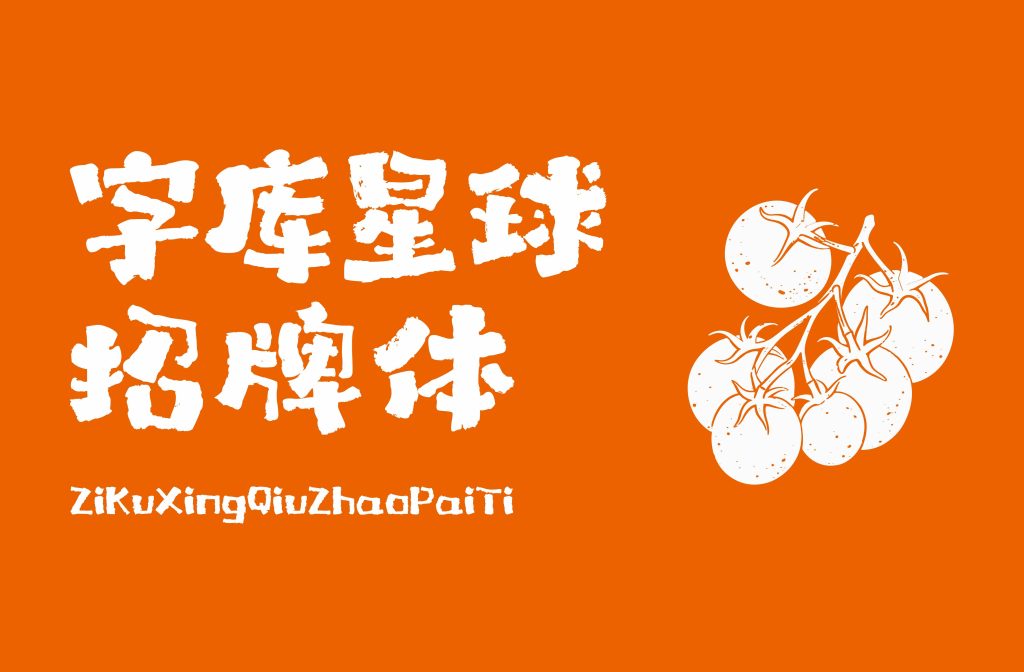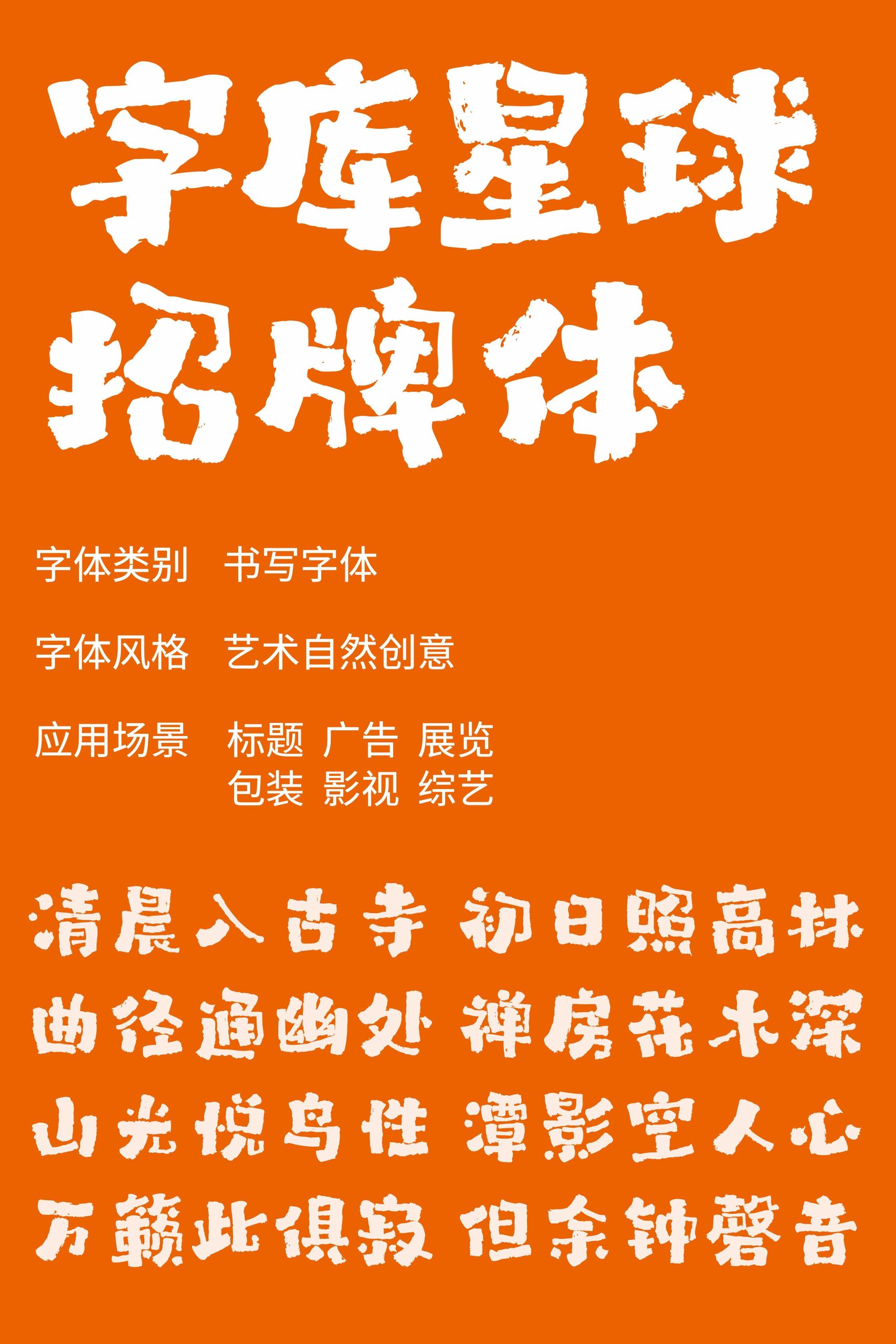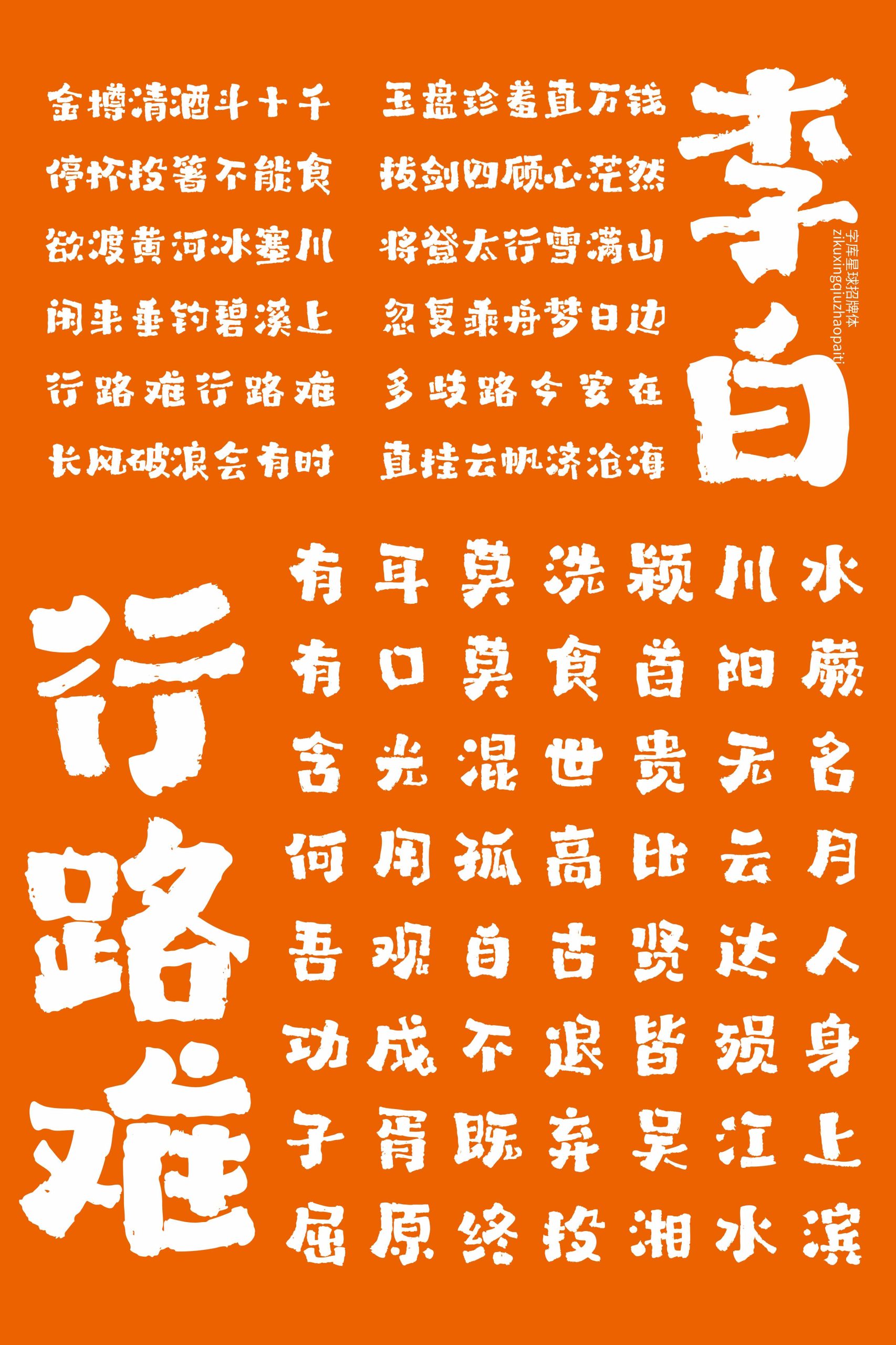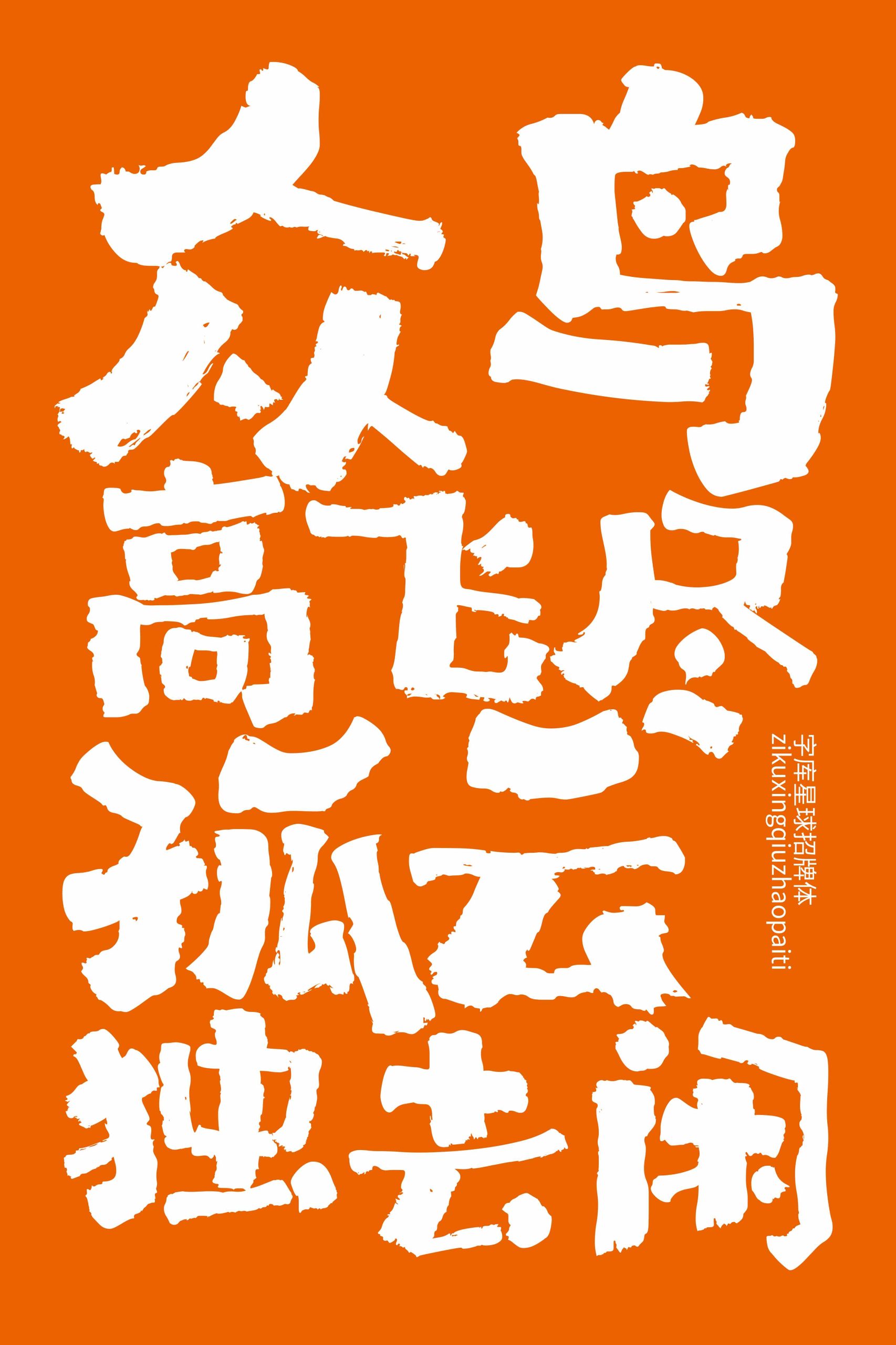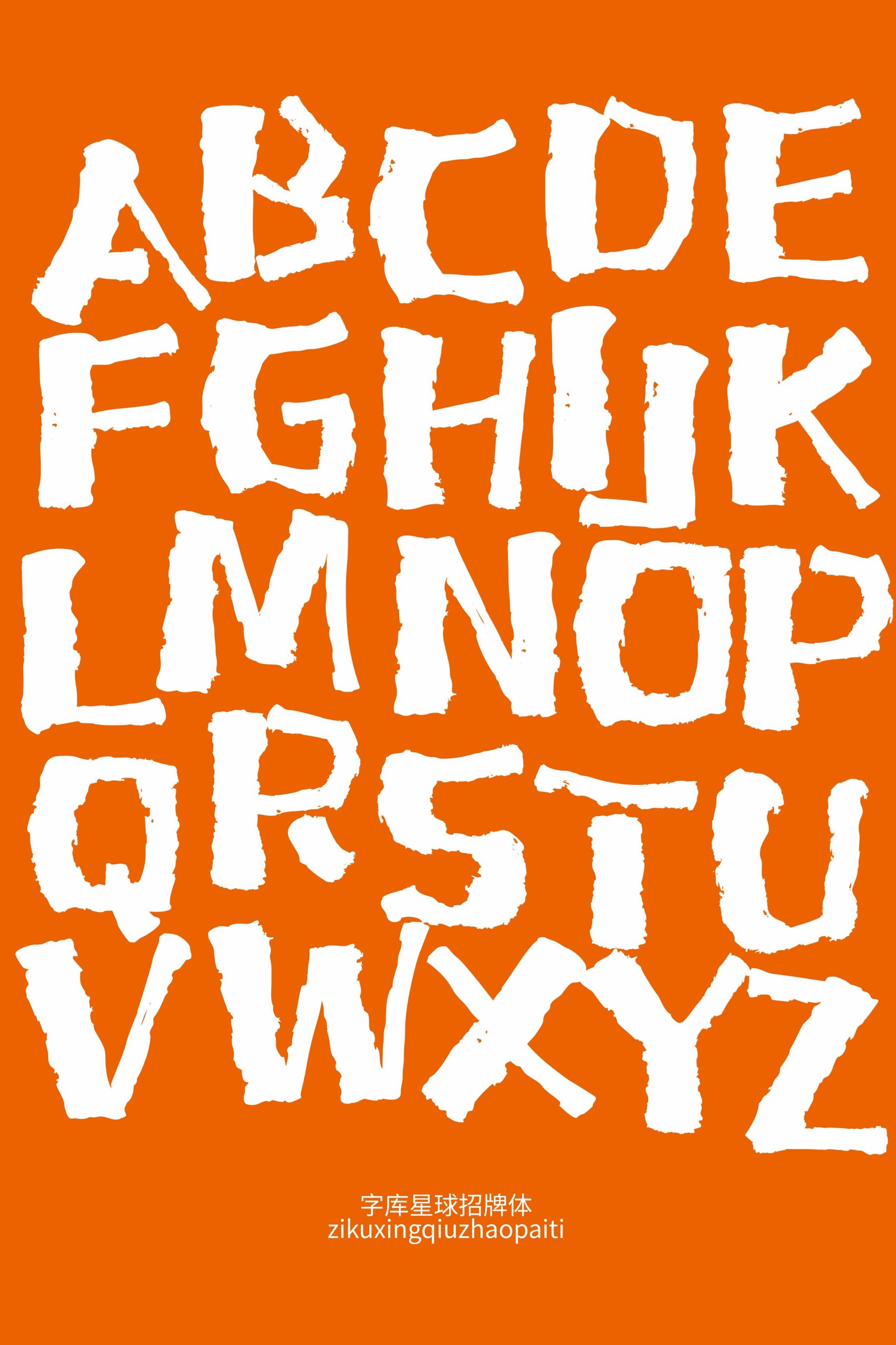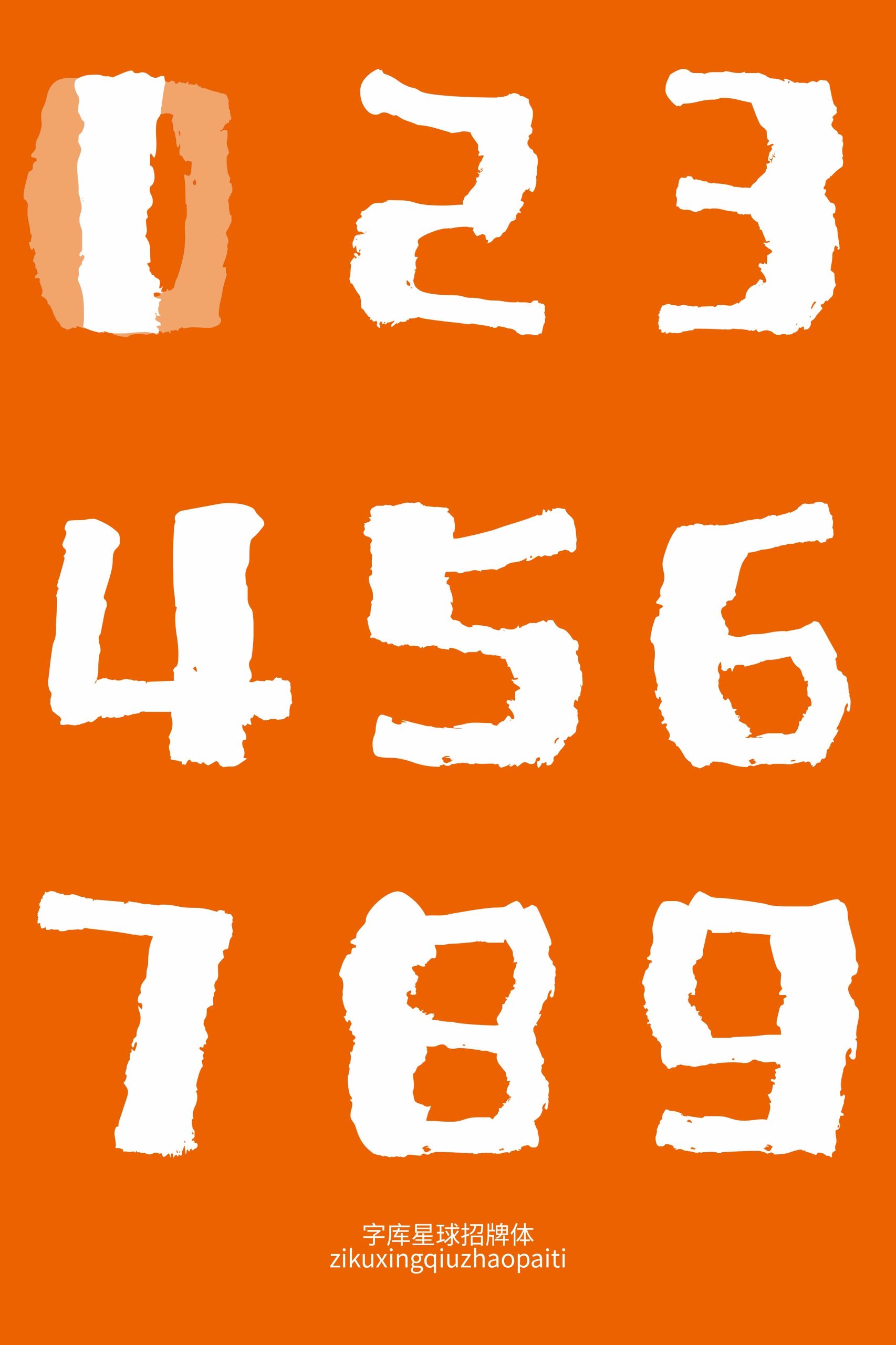
不知道你有没有留意老街上的老店招牌,没有千篇一律的工整模板,手写笔墨松弛随性,藏着最动人的市井烟火。今天给大家带来字库星球招牌体,一款浸润人间温度的老街毛笔手书字体,把街巷里的鲜活气韵,完整装进字库。
笔触松弛自然,酣畅醇厚,字形洒脱自在。笔画拥有强烈的粗细对比,刚柔并济、收放自如,拒绝刻意规整的工业感。笔墨浓淡虚实流转,字里行间藏着寻常日子的酸甜苦辣,浑厚接地气,满是真实的生活质感。它张扬却不凌厉,自带亲和治愈的底色,无论是复古老街氛围感,还是烟火食铺、生活纪实的视觉调性,都可以轻松拿捏,将平淡的人间烟火,实实在在落在纸面。
西文字形沿用同源毛笔笔意,方正舒展,中英文浑然相融,整体格调高度统一。适合小吃门店、老店门头、土特产招牌,也适配时令佳节海报、民俗庆典物料、市井商招、休闲文娱设计,笔墨落处,满堂喜乐,尽显人间红火祥和之意。